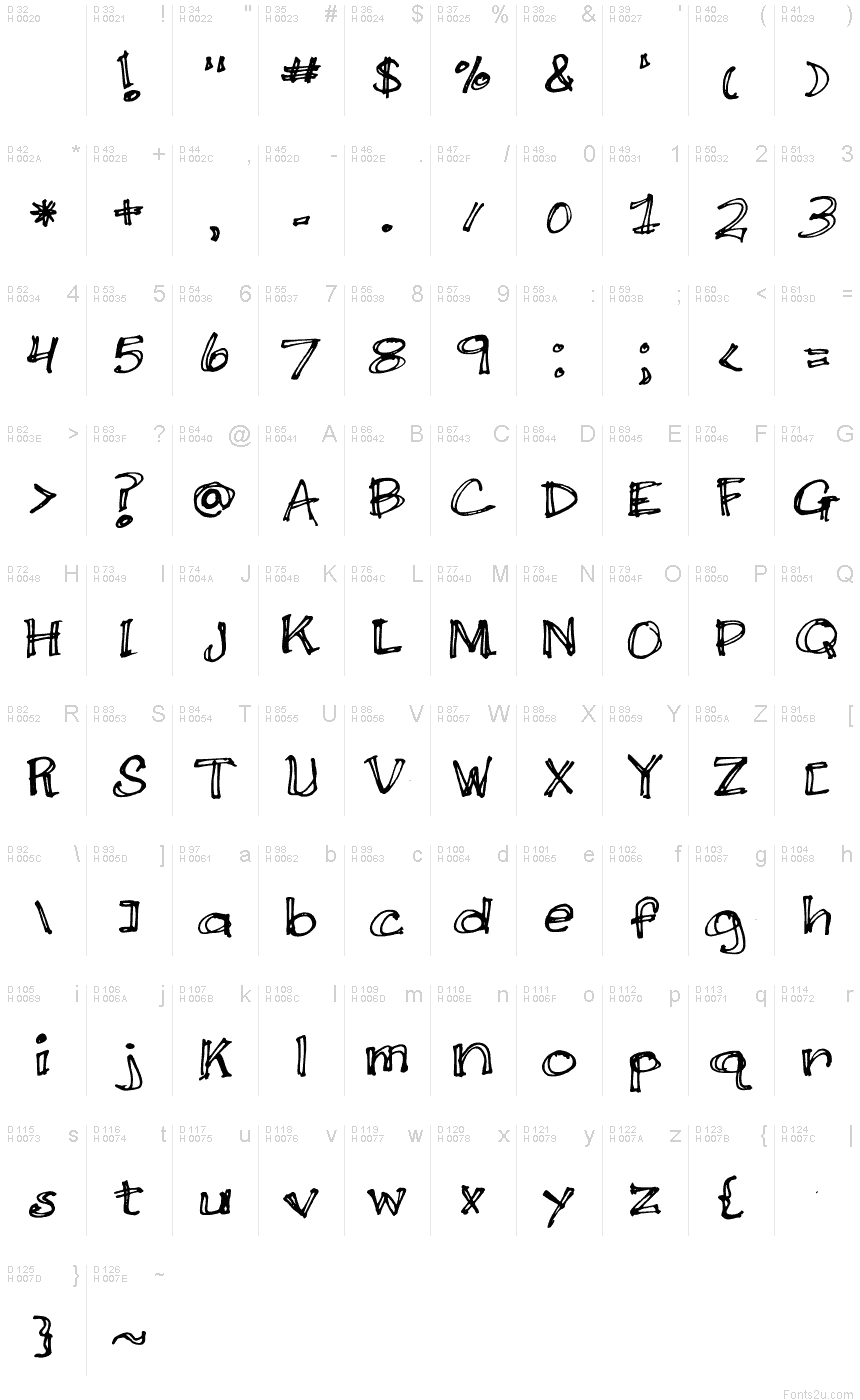
Double Scratch, stworzony przez Brittney Murphy, to darmowy, odręczny krój pismo typu display o luźnych, zakreślonych konturach. Jego wysokie, nieregularne litery łączą zaokrąglone pętle z tępymi pociągnięciami pionowymi i surowym efektem podwójnego rysunku. Pismo sprawia wrażenie pośpiesznego i niedbale bazgrane.
Double Scratch pasuje do bazgrołów, ilustracji markerem i szkicowanych ikon w grafikach młodzieżowych, plakatach w stylu komiksowym oraz niezależnej oprawie muzycznej DIY. Powtarzający się kontur nadaje etykietom i gadżetom domowy charakter w stylu „długopis na papierze”, zamiast czystego, cyfrowego wykończenia. Może również kształtować wizerunek nieformalnych klubów artystycznych lub stoisk rzemieślniczych lokalnych twórców, gdzie liternictwo staje się częścią rysowanej tożsamości.